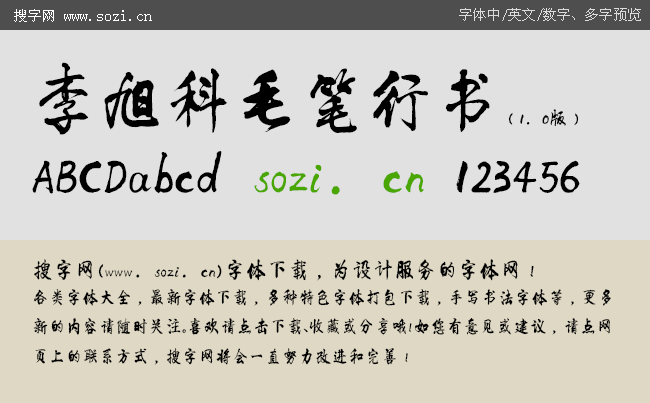
李旭科毛筆行書
搜字網(wǎng)提供一款李旭科毛筆行書中文書法字體下載,李旭科毛筆行書是一款手寫風(fēng)格的行書書法中文字體,該字體書寫流暢,瀟灑大方,整體效果十分出色。適合應(yīng)用于廣告設(shè)計、名片設(shè)計、包裝印刷、產(chǎn)品設(shè)計等應(yīng)用。